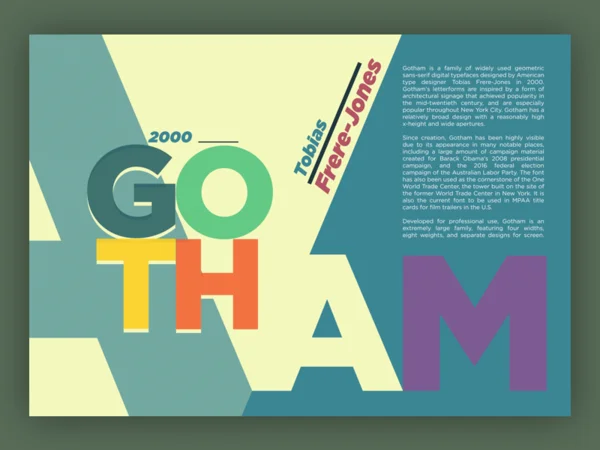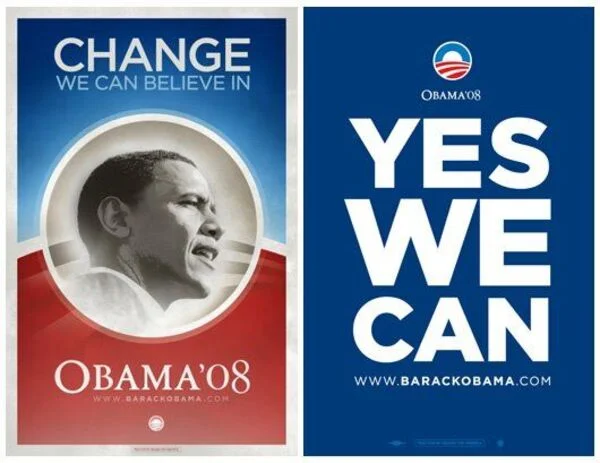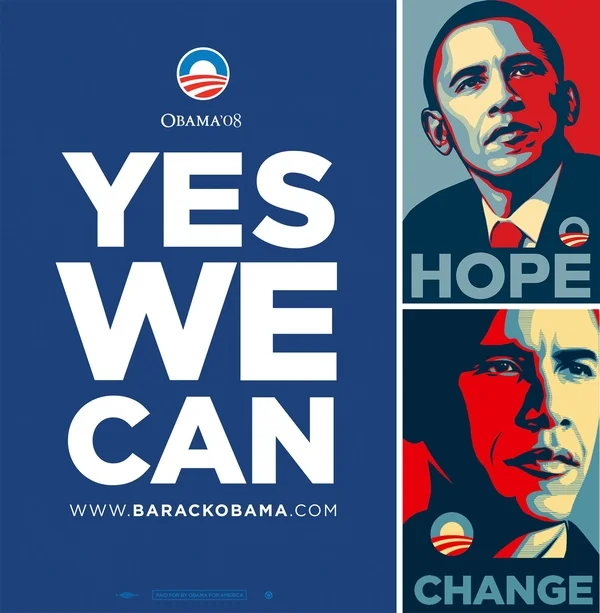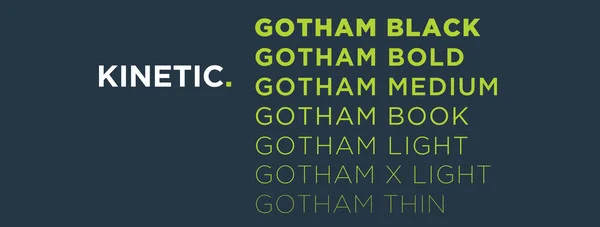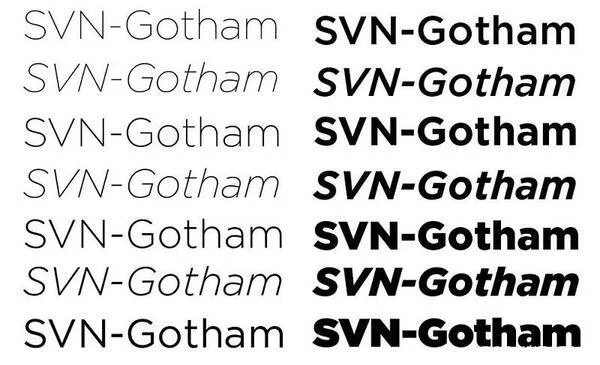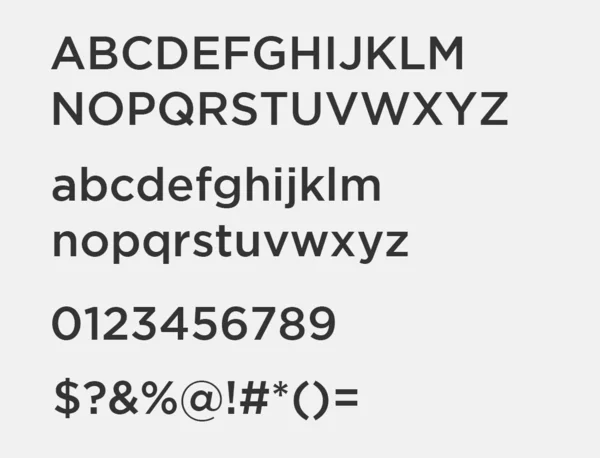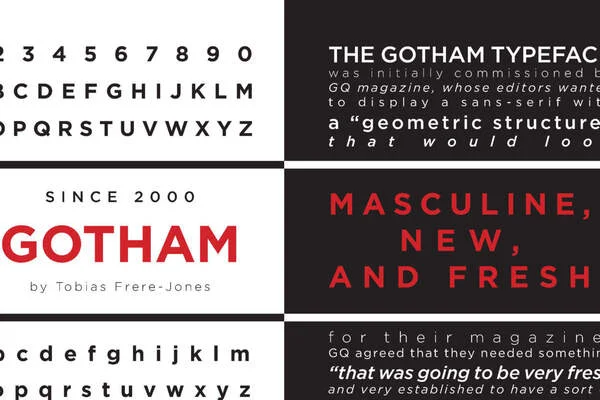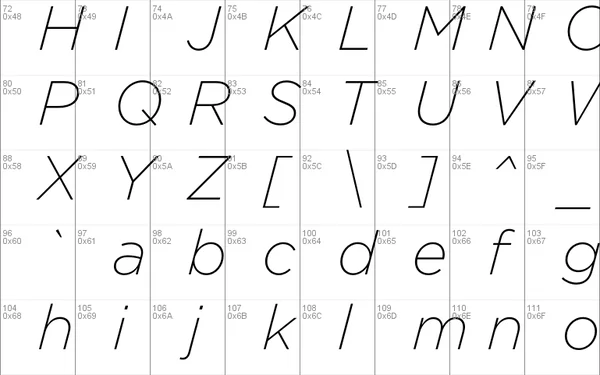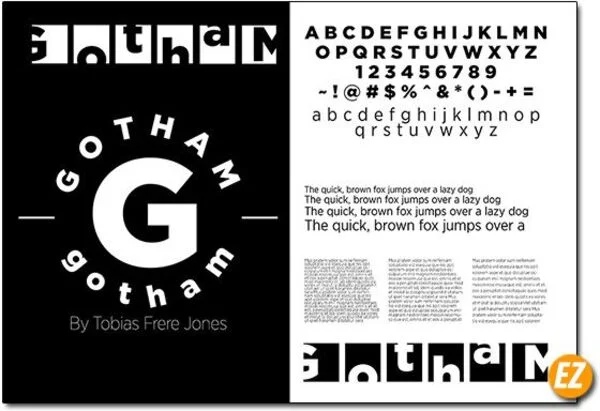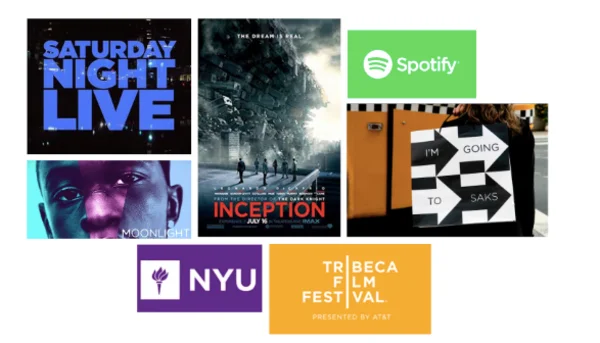
Font chữ là một trong những công cụ quan trọng nhất đối với mỗi designer hay ngành thiết kế đồ hoạ. Font Gotham hay font SVN Gotham là một trong những font chữ đẹp và được ưa chuộng nhất. Vì vậy, Printgo xin giới thiệu sơ lược về font SVN Gotham và gửi đến các bạn file tải font Gotham ở cuối bài viết.
Font Gotham ra đời vào năm 2000, là một tác phẩm của nhà thiết kế người Mỹ Tobias Frere Jones. Font SVN Gotham là bộ font Gotham đã được Việt hoá. Mẫu font Gotham này được lấy cảm hứng từ những tấm biển hiệu giữa thế XX và rất phổ biến ở thành phố New York.
Với phong cách mạnh mẽ, font Gotham được sử dụng rất nhiều cho các chiến dịch đáng chú ý, trong đó phải kể đến chiến dịch tranh cử tổng thống của Barack Obama năm 2008, giúp nâng tầm đẳng cấp cho font chữ này.